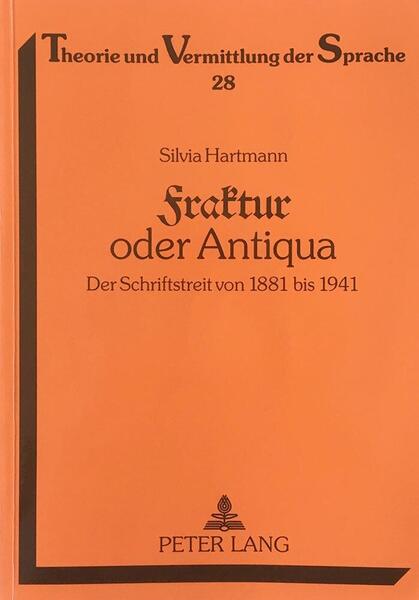
Schon im 16. Jahrhundert bildete sich im deutschsprachigen Raum ein paralleles Auftreten zweier Schriftstile der lateinischen Schrift heraus: Antiqua und gebrochene Schrift. Aus dieser Zweischriftigkeit entwickelte sich frühzeitig eine Auseinandersetzung um die Frage, welche der beiden Schriftformen für deutschsprachige Texte zu verwenden sei. Seinen Höhepunkt erreichte der Streit im ausgehenden 19. Jahrhundert und hielt bis zur De-facto-Abschaffung der gebrochenen Schriften als Verkehrsschrift im Jahr 1941 an. Das Buch »Antiqua oder Fraktur« von Silvia Hartung beleuchtet diese Phase des Antiqua-Fraktur-Streits. Ausgangspunkt bilden die Bestrebungen für die Antiqua um den Altschriftverein von Friedrich Soennecken, die Anfang des 20. Jahrhunderts auch im Reichstag zur Debatte stehen. In der Folge wird der 1918 gegründete und bis 1941 bestehende Bund für deutsche Schrift als wesentlichen Gegenspieler ausführlich beleuchtet: seine Personen, die Vereinsarbeit, die Publikationen, die Kommunikation mit den jeweiligen Machthabern usw.
Ein weiteren Schwerpunk bildet schließlich die Schriftpolitik der Nationalsozialisten zwischen 1933 und 1941. Über die Untersuchung der erhaltenen Schriftwechsel werden die Position von Einzelpersonen und Ministerien zum Schriftstreit umfassend aufgearbeitet. Die wesentlichen Dokumente sind auch im circa 100 Seiten starken Anhang abgebildet.
Das Buch wurde von Silvia Hartmann im Fachbereich Sprach- und Literaturwissenschaft der Universität-Gesamthochschule Siegen als Dissertation verfasst und bildet die wohl bislang umfangreichste Aufarbeitung der letzten Phase des Antiqua-Fraktur-Streits. Wie für eine kulturwissenschaftliche Arbeit selbstverständlich, erfolgt die Darstellung faktenreich und neutral auf Basis der vorhandenen Quellen. Somit bildet das Buch eine empfehlenswerte Darstellung für alle, die sich über den Antiqua-Fraktur-Streit, die Schriftpolitik des NS-Regimes bzw. die früheren Aktivitäten des Bundes für deutsche Schrift informieren möchten.